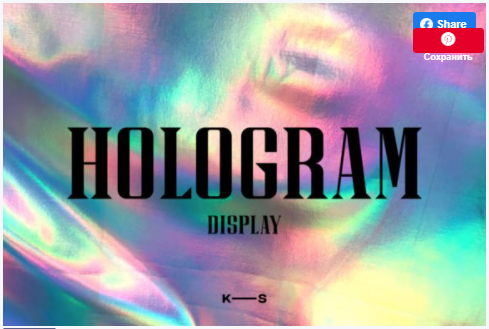
Hologram Font
Голограмма - это жирный и напористый двойной шрифт (с засечками и без засечек). Поддайтесь его особому стилю и используйте его для создания веб-дизайнов, визиток и многого другого, что требует уникального подхода.